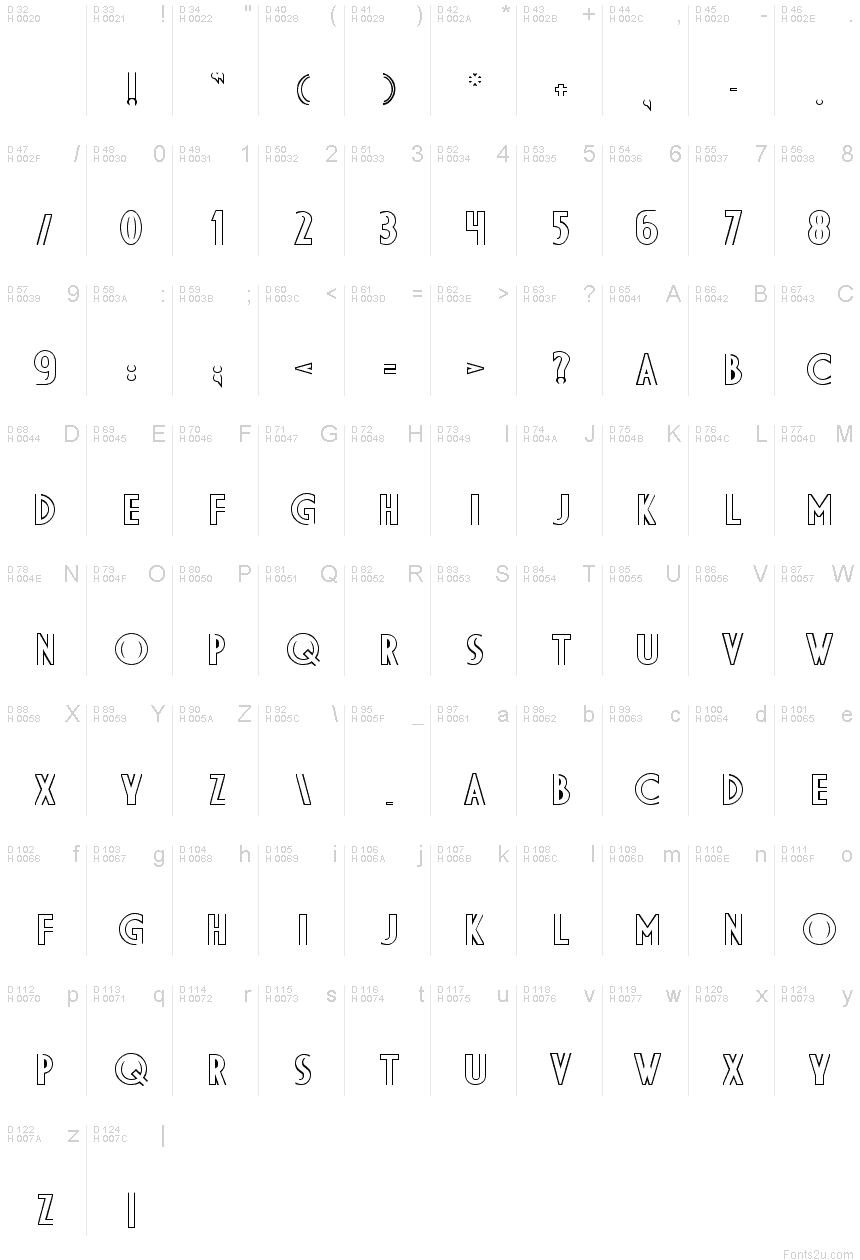
Krój DS Diploma-DBL Bold od DS Diploma wprowadza ten wyrazisty, akademicki klimat z czystym, konturowym designem, który pozostaje lekki nawet przy dużych rozmiarach. W rodzinie DS Diploma-DBL pociągnięcia przypominają zakreślone rurki: są zaokrąglone, stabilne i mają pewny odstęp, dzięki czemu nagłówki czyta się szybko, nie zlewają się one w czarny blok. To darmowy, dekoracyjny krój konturowy.
DS Diploma-DBL Bold świetnie sprawdza się w dyplomach, zaproszeniach na zakończenie roku, gadżetach szkolnych, logotypach w stylu varsity, plakatach wydarzeń, grafikach na odznaki czy przyciągających wzrok nagłówkach w mediach społecznościowych. Ten darmowy font błyszczy, gdy dasz mu przestrzeń – wypróbuj go w dużym rozmiarze, dodając jednolite wypełnienie lub delikatny cień za konturem dla dodatkowego efektu. Połącz go z prostym krojem bezszeryfowym, takim jak Inter, aby zachować czystość tekstu towarzyszącego.